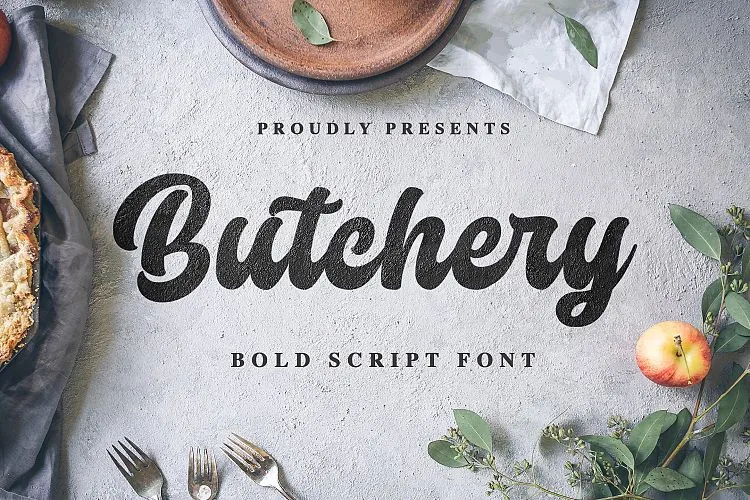
Butchery Script Font – Download Grátis
A C00zona nos apresenta Hello!, uma fonte script rica e feminina, perfeita para estilos criativos e elegantes que valorizam a mulher. Ideal para designers buscando adicionar um toque especial às publicações de casamentos, Hello! oferece um formato gráfico único e sofisticado. Para quem busca algo ainda mais potente e retrô na categoria do script bold, a C00zona lança Butchery Font. Inspirada nas poster de comida, menus e embalagens alimentares, esta fonte traz uma paleta vibrante que se assemelha à arte moderna dos velhos tempos da gastronomia. Se você busca incorporar um design único e inovador às suas criações gráficas, Butchery é a escolha perfeita. Seja para logotipos de comidas, cartazes alimentares, menus ou embalagens – esta fonte oferece uma variedade infinita de possibilidades. Se você está em busca de uma fonte que não apenas complementará seu design mas o fará brilhar ainda mais, entremos no universo retro e feminino da Butchery Font.